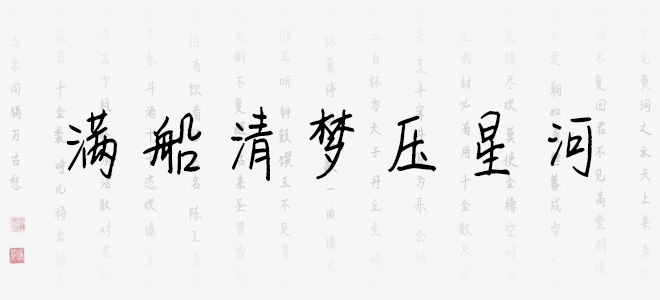
滿船清夢(mèng)壓星河ttf是麥拉風(fēng)字庫推出的一款手寫風(fēng)格藝術(shù)字體,字體筆觸粗細(xì)適中,書寫流暢,適合應(yīng)用于藝術(shù)設(shè)計(jì)、平面宣傳設(shè)計(jì)、網(wǎng)頁設(shè)計(jì),書法字帖等領(lǐng)域,歡迎喜歡滿船清夢(mèng)壓星河字體的朋友前來下載使用。
麥拉風(fēng)滿船清夢(mèng)壓星河